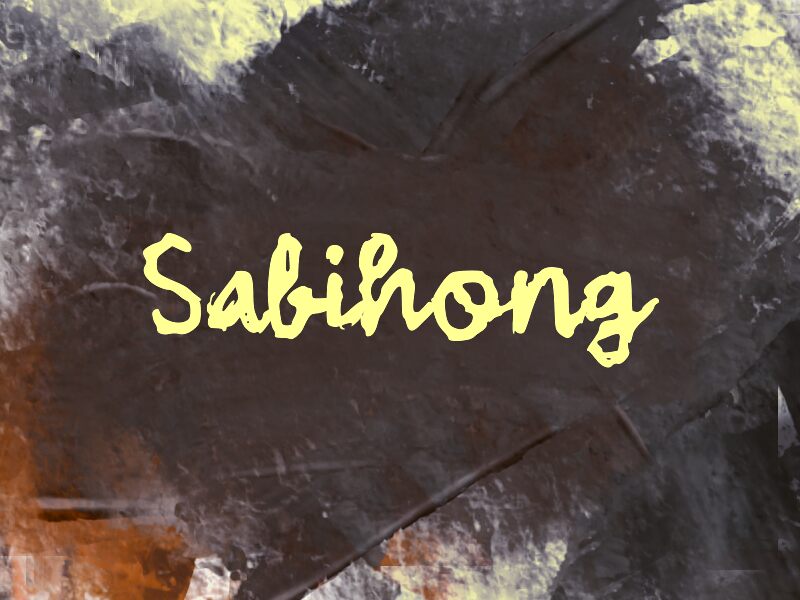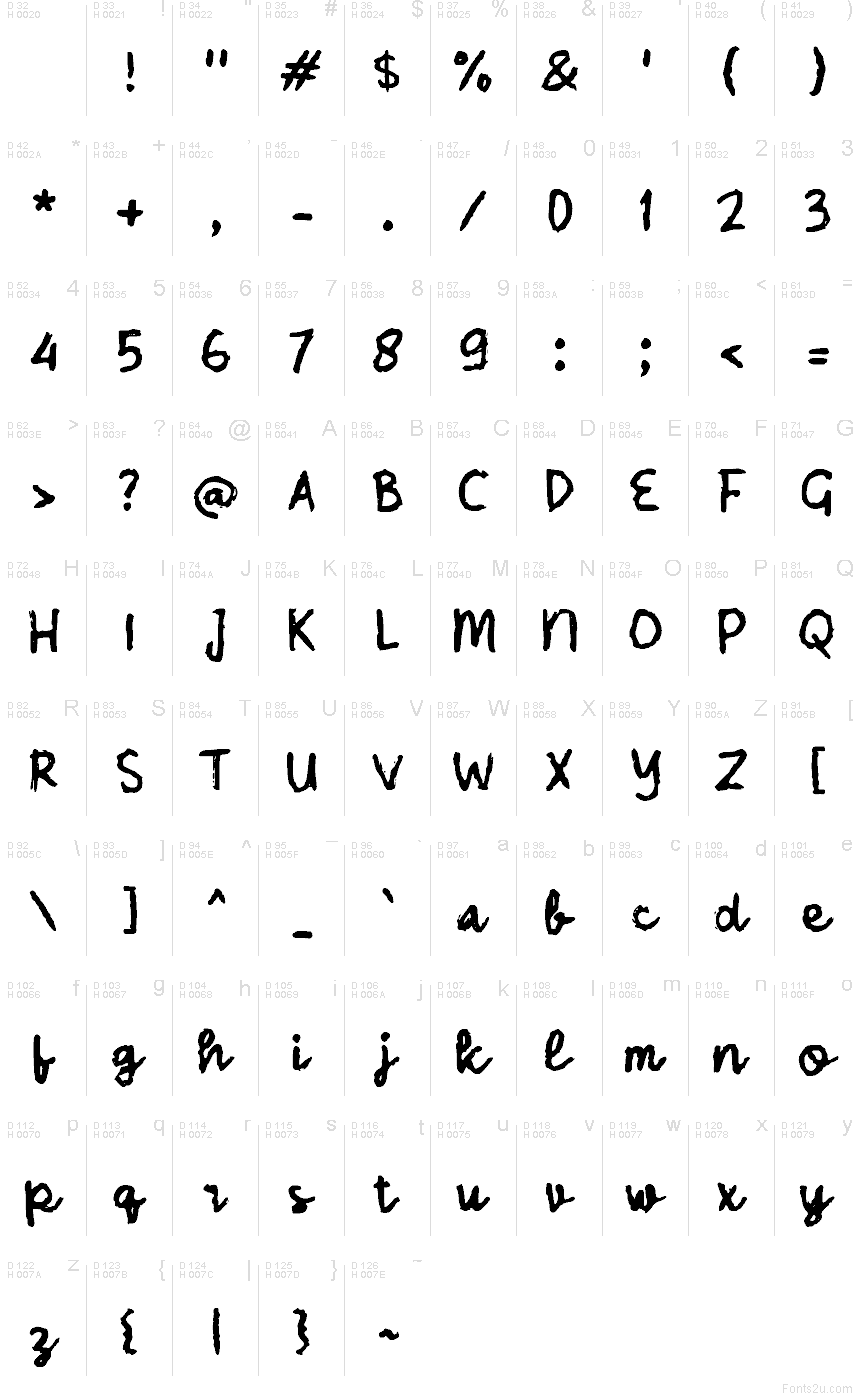
Sabihong 字体
Sabihong
Sabihong 由 Wep 设计,是一款免费的“trash”风格标题字体。它有着厚实的笔触、饱满的曲线和粗糙的边缘,仿佛在湿漉漉的墨迹中拖拽而成。不规则的轮廓赋予了字体一种街头艺术般的节奏感,比起工整的装饰风格,它更像是未经修饰的涂鸦作品。
这种躁动不安的质感非常适合用于音乐传单、滑板图形、海报大标题、杂志封面以及硬核街头品牌设计,因为在这些场景中,过于平滑的字体反而显得格格不入。短标题和标志性的字标最能展现其魅力,斑驳的轮廓和戛然而止的笔画末端,为每一行文字注入了强烈且真实的手绘存在感。